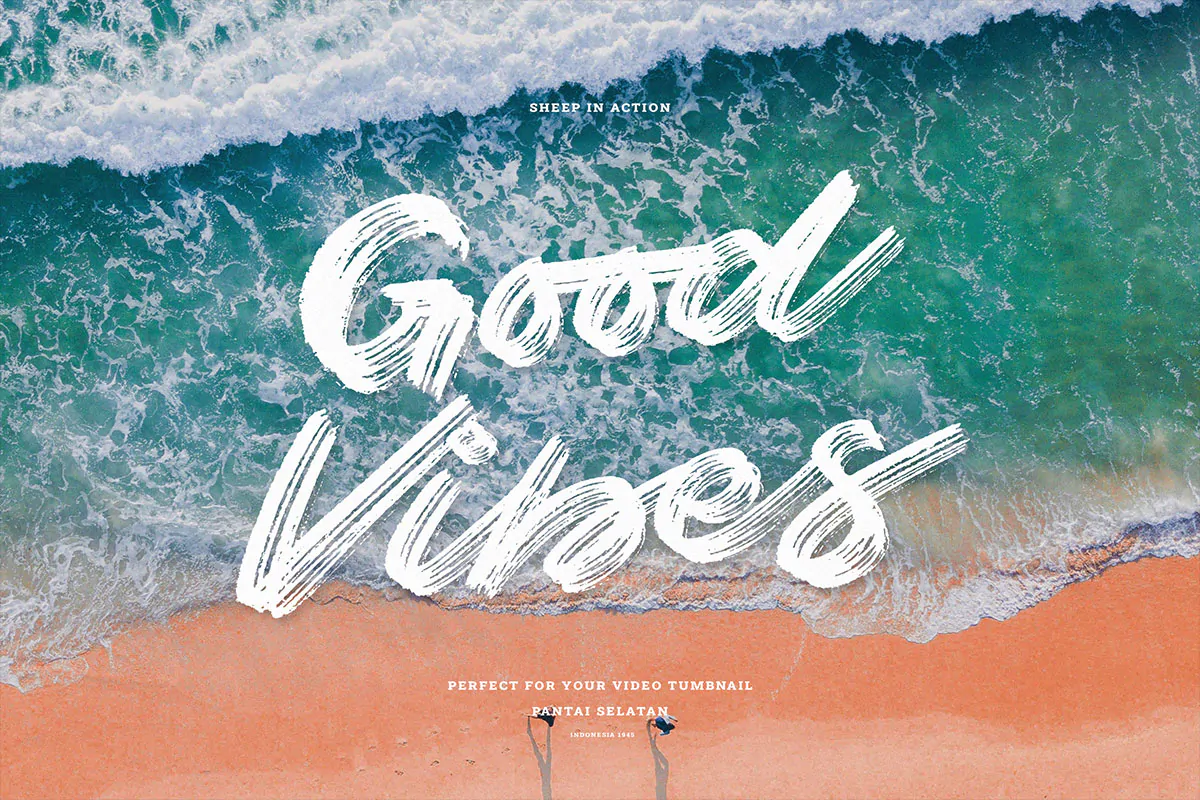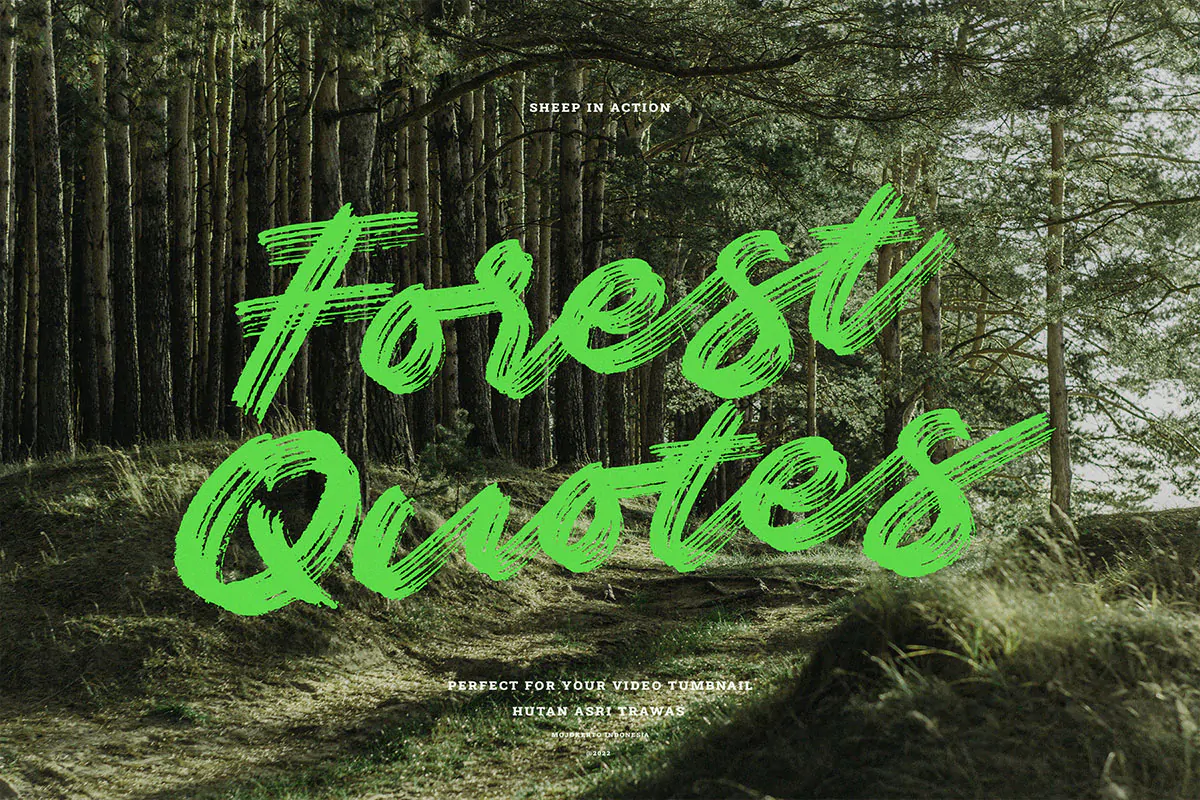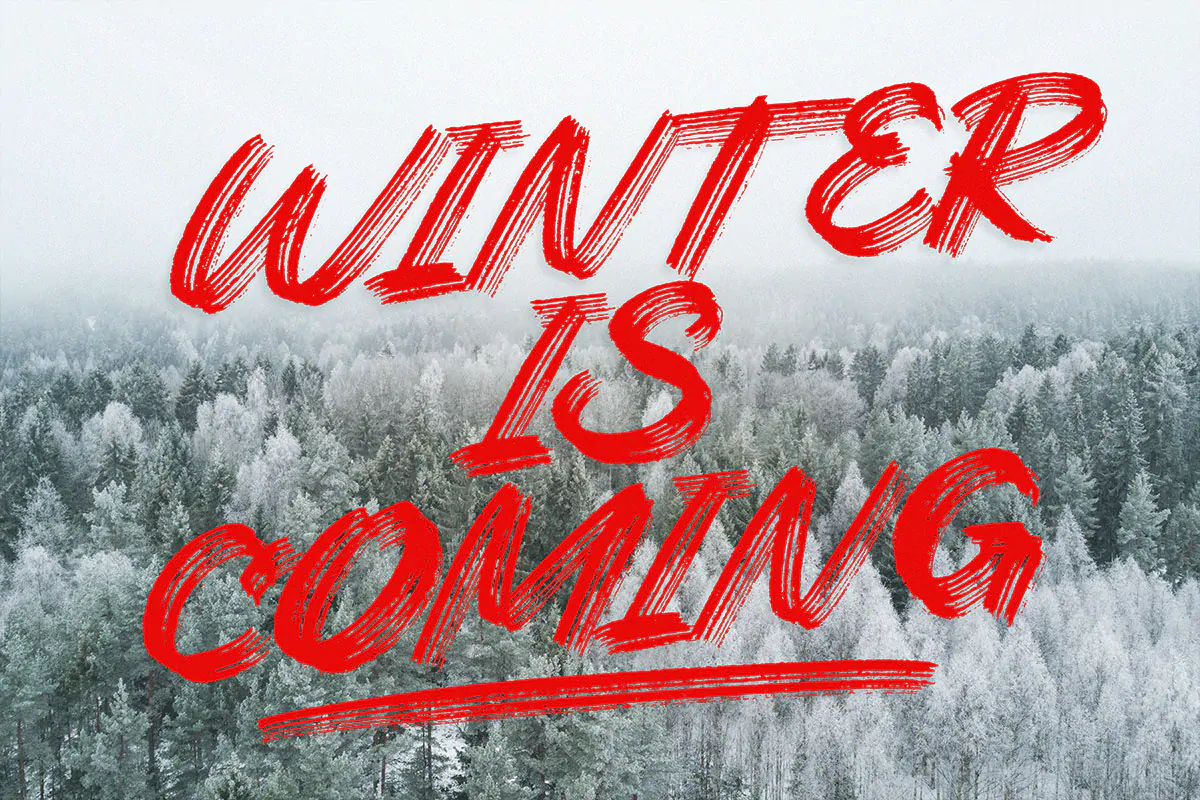
فونت سبک قلمو Sheep (براش فونت)
فونت سبک قلمو
فونت سبک قلمو Sheep (براش فونت) یک اسکریپت فونت فوق العاده زیبای انگلیسی است که مناسب برای استفاده در طراحی انواع پوستر، کارت ویزیت، بنر، بسته بندی محصولات، ظروف یکبار مصرف و دیگر پروژههای گرافیکی میباشد.